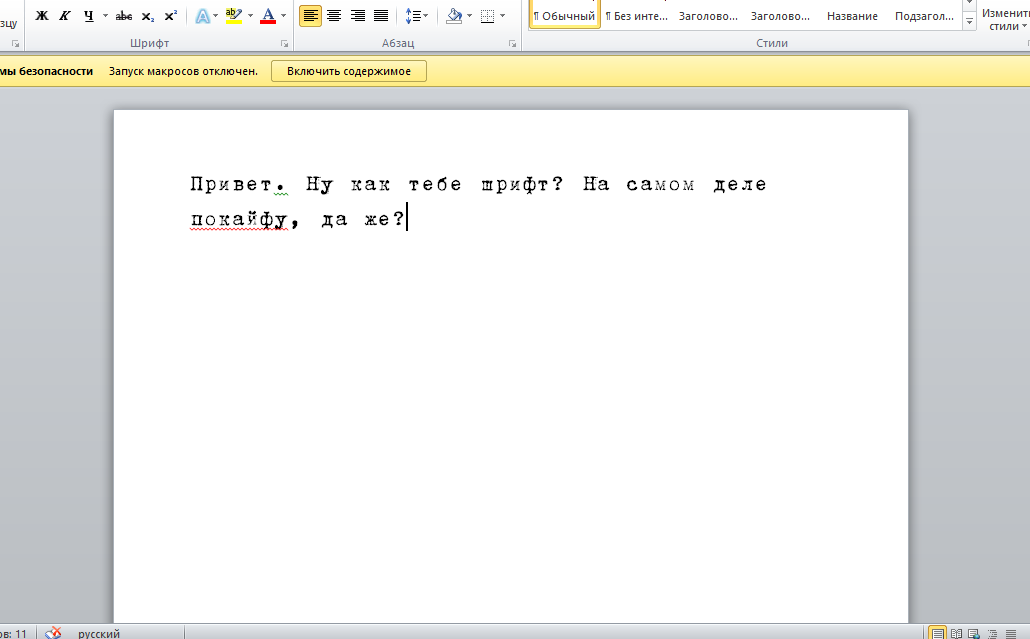
Кириллические шрифты в стиле «печатной машинки» для Photoshop
Шрифты в стиле «печатная машинка» могут быть использованы для создания ретро-дизайна. В данной подборке собраны 20 кириллических шрифтов, которые могут помочь привлечь дух прошлого в ваши проекты.
a_OldTyperNrRegular
Шрифт с весьма витиеватым начертанием, округлыми буквами и засечками. Тайкой использовался на некоторых видах печатных машинок.
DS_moster
Шрифт, который нельзя спутать ни чем другим. Имеются даже грязь и кляксы от отпечатывания букв.
TrixieCyr-Cameo
Каждая буква данного шрифта имеет черный фон, таким образом, создается имитация печатного текста.
TrixieCyr-Light
Еще один вариант «печатного» стиля, для тех вариантов, когда чернила в машинке заканчиваются, и буквы не полностью пропечатываются. Поэтому много светлых участков в каждой букве, серость общего вида, несмотря на использование черного цвета.
B52
Один из самых известных шрифтов в стиле «печатной машинки». Создан он был в конце 90-х годов прошлого столетия и до сих является самым востребованным. Буквы имеют небольшие кляксы и точки от чернил.
Например, при создании текста в поле вверху он будет генерировать Список символы и буквы привлекательно для копирования и вставки.
То, что вы наблюдаете на своем устройстве, может быть необычным при использовании других устройств. Это происходит из-за того, что каждый жанр устройств имеет свой способ переосмысления этого Unicode или что он еще не поддерживает эти символы.
Это не означает, что в этом инструменте есть ошибка, это означает, что шрифт, выбранный для использования на сайте, не поддерживает этот символ. Но есть набор персонажей, которые, если они соответствуют дизайну и стилю, как они есть:
✍ Конвертер букв пишущей машинки
🎈 ᕼ𝐞ℓ𝓵Ⓞ ♞ඏ
🐤🐳 卄 𝐞ℓ ㄥ ᗝ 💣💢
→ Код Unicode: что это такое?
Что такое Юникод? Это Международный стандарт который позволяет компьютерам (и другим устройствам) интерпретировать и использовать текстовые символы из любой системы письма.